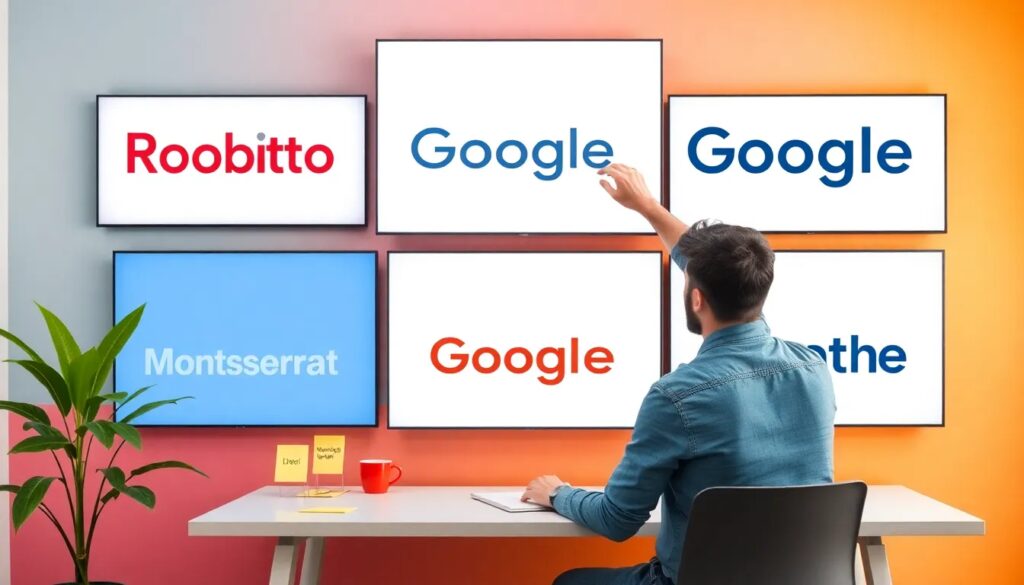
Top Google Fonts para 2026
Las tipografías juegan un papel crucial en el diseño web y gráfico. Una de las opciones más completas y accesibles son las Google Fonts, que ofrecen una amplia gama de estilos y diseños. Este artículo presenta una selección de las 40 mejores fuentes de Google, ideal para mejorar tus proyectos en línea.
Exploraremos las características de estas fuentes, cómo utilizarlas y las combinaciones más efectivas. Si estás buscando las mejores opciones para 2026, estás en el lugar adecuado.
¿Qué son las Google Fonts y por qué usarlas?
Las Google Fonts son una biblioteca extensa de fuentes tipográficas de código abierto que puedes utilizar de manera gratuita. Su uso ha crecido exponencialmente debido a su calidad y facilidad de integración en proyectos web.
Uno de los principales beneficios de utilizar Google Fonts es la optimización de la carga. Al usar su API, las fuentes se cargan de manera rápida y eficiente, lo que contribuye a una mejor experiencia de usuario.
- Compatibilidad con múltiples navegadores y dispositivos.
Además, las Google Fonts permiten a los diseñadores explorar diversas familias tipográficas que pueden adaptarse a diferentes estilos y propósitos, desde diseños minimalistas hasta llamativos.
¿Cuáles son las 40 mejores Google Fonts para mejorar el diseño de tu página web?
En esta sección, te presentamos una selección de las 40 mejores Google Fonts que pueden transformar el diseño de tu página web. Estas fuentes han sido elegidas por su versatilidad y atractivo visual.
- Roboto - Ideal para interfaces modernas.
- Alegreya - Perfecta para textos largos.
- Merriweather - Una opción excelente para la legibilidad.
- Lato - Muy popular por su estilo limpio.
- Poppins - Con un diseño geométrico atractivo.
- Open Sans - Versátil y amigable para la web.
- Oswald - Una excelente opción para títulos.
- Montserrat - Moderna y elegante, ideal para encabezados.
- Raleway - Tipografía estilizada y delgada.
- Source Sans Pro - Ideal para texto técnico.
Estas fuentes son perfectas para diversos proyectos, desde blogs hasta sitios de comercio electrónico. Muchas de ellas ofrecen múltiples pesos y estilos, permitiendo mayor creatividad en el diseño.
¿Qué tipografías bonitas se pueden encontrar en Google Fonts?
Hay una amplia variedad de tipografías bonitas en Google Fonts, ideales para añadir un toque estético a tus proyectos. Algunas de las más destacadas son:
- Quicksand - Con un diseño redondeado y amigable.
- Playfair Display - Perfecta para un estilo más clásico.
- Pacifico - Una opción informal y divertida.
Estas fuentes no solo son visualmente atractivas, sino que también mejoran la legibilidad, lo que es crucial para una buena experiencia de usuario.
¿Cuáles son las combinaciones de Google Fonts más recomendadas?
Combinar diferentes fuentes puede ser un desafío, pero hay algunas combinaciones que funcionan excepcionalmente bien. Aquí te presentamos algunas recomendaciones:
- Roboto + Merriweather - Funciona bien para títulos y textos.
- Poppins + Open Sans - Ideal para un diseño moderno y limpio.
- Playfair Display + Raleway - Perfecta para un estilo elegante.
Recuerda que la combinación de diferentes estilos puede aportar a tu diseño un aire fresco y profesional. Asegúrate de que las fuentes elegidas sean complementarias en términos de estilo y peso.
¿Qué otras fuentes modernas están disponibles en Google Fonts?
Aparte de las fuentes más populares, Google Fonts cuenta con una amplia gama de opciones modernas. Algunas de las más notables son:
- Archivo - Ideal para proyectos que buscan un estilo contemporáneo.
- Barlow - Con un diseño arquitectónico y limpio.
- Zen Kaku Gothic New - Para un estilo único y llamativo.
Estas fuentes son perfectas para quienes buscan un enfoque más moderno y contemporáneo en sus diseños, aportando un toque fresco a cualquier proyecto.
¿Cuáles son las mejores prácticas para usar Google Fonts en tu proyecto?
Para sacar el máximo provecho de las Google Fonts, considera las siguientes mejores prácticas:
- Selecciona solo las fuentes que realmente necesitas para minimizar la carga de tu página.
- Utiliza los estilos adecuados para asegurar una buena legibilidad, especialmente en dispositivos móviles.
- Verifica la compatibilidad con diferentes navegadores y dispositivos.
Implementar estas prácticas no solo mejora la estética de tu sitio, sino que también optimiza la experiencia del usuario y el rendimiento general de la página.
Para ver más sobre el uso de Google Fonts, puedes explorar este recurso visual que muestra cómo estas tipografías pueden mejorar tu diseño:
En conclusión, las Google Fonts son herramientas esenciales para cualquier diseñador digital que busque calidad y versatilidad en sus proyectos. Con una amplia variedad de fuentes disponibles, seguro encontrarás la opción perfecta para tu página web. ¡No dudes en experimentar y encontrar las combinaciones que mejor se adapten a tu estilo!